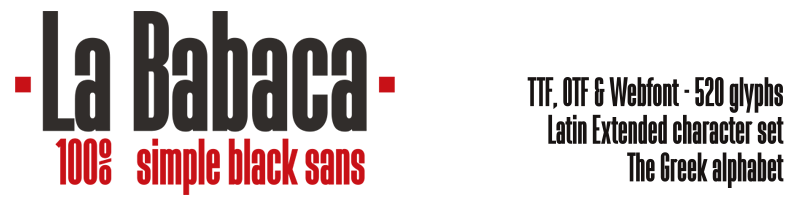
Font name: | La Babaca |
La Babaca es una tipografía black, sin serif y comprimida de formas geométricas muy simples, sin adornos, una fuente display sobria, que proporciona un gran ahorro de espacio para títulos grandes. =========== The babaca is a black typeface without serifs and compressed very simple geometric shapes, unadorned sober display font that provides a great space saver for big titles. =========== • Descarga gratis las versión completa de la fuente desde mi web (520 glyphs) • Letras griegas • Números disponibles en mi web. • Letras alternativas • Sólo para uso personal. • Licencia comercial disponible: webfont + funciones Open type • Download the full version from my website.(520 glyphs) • Greek characters • Numbers available on my website. • Alternative characters • Only for personal use. • Commercial license available: webfont + OpenType functions: http://defharo.com/fonts/la-babaca-font/ =========== |